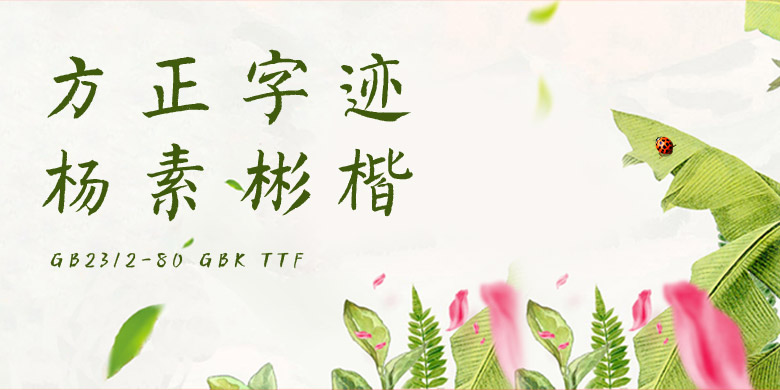
方正字迹-杨素彬楷 简
作者杨素彬,河北省书法家协会会员,河北省公安文学艺术联合会会员,河北省青少年书画家协会研究员。书法篆刻作品曾获河北省第二节艺术节三等奖。书法作品曾获河北省首届群众书法大赛二等奖。所书写的此套字库,源于唐颜真卿颜勤礼碑,书写时进行了再创作,且保留了颜体楷书的基本特征。结构上端庄雍容宽博大气,而书写时加快了速度,增添了灵活性。整体更具时代感。